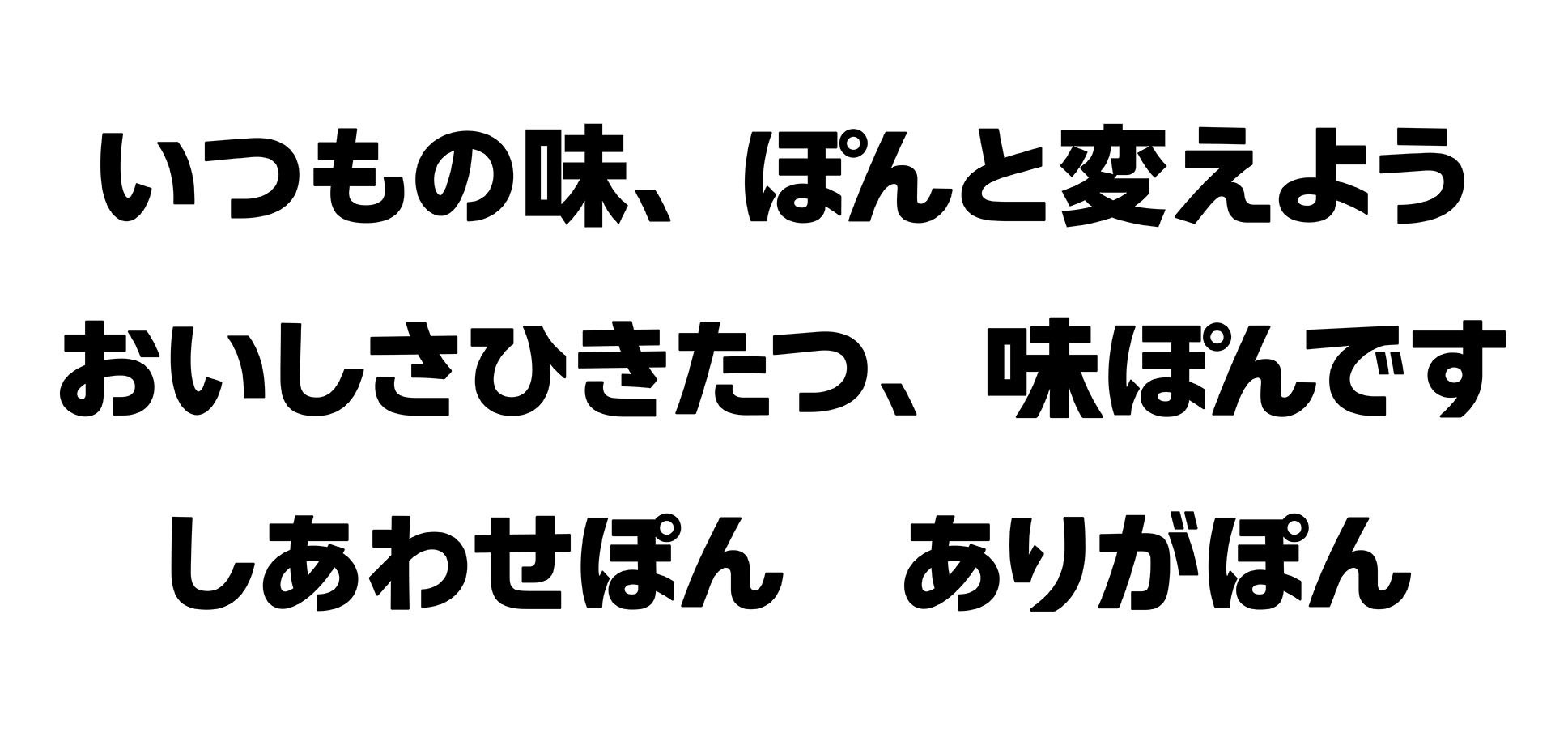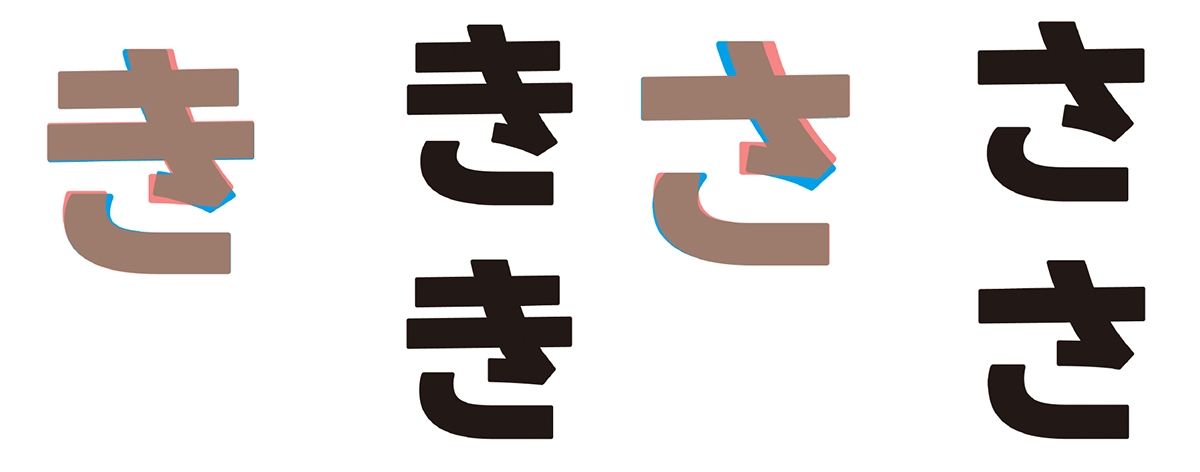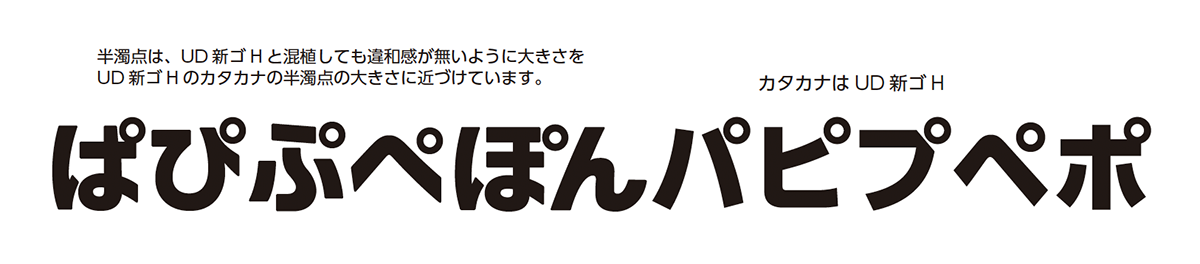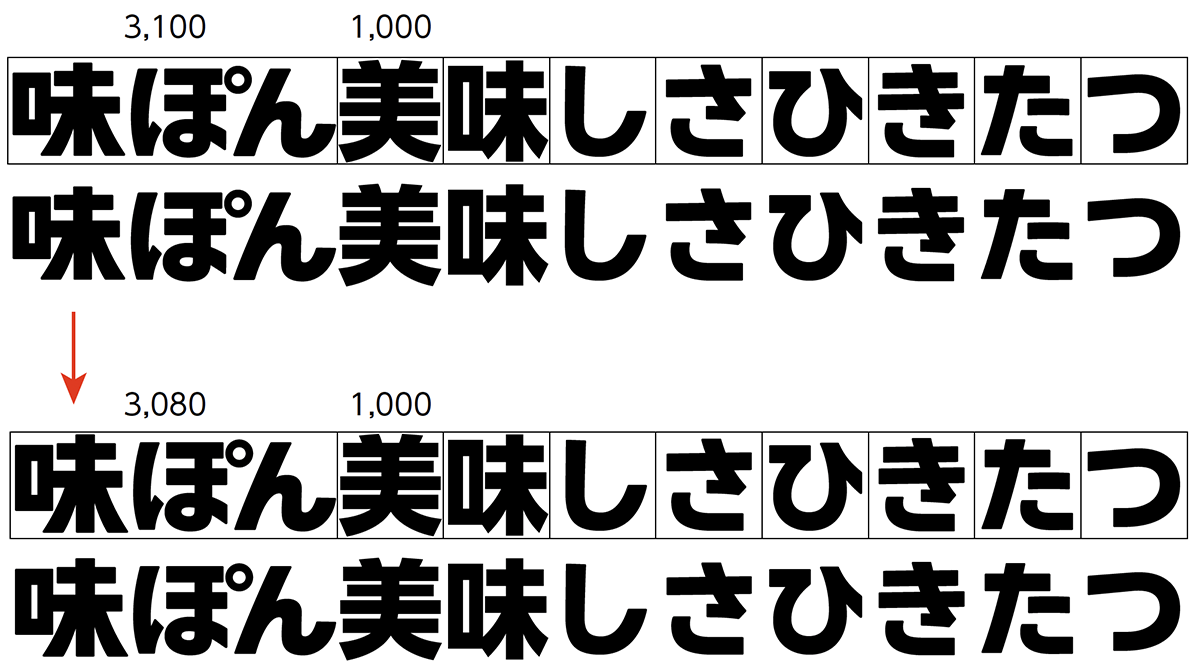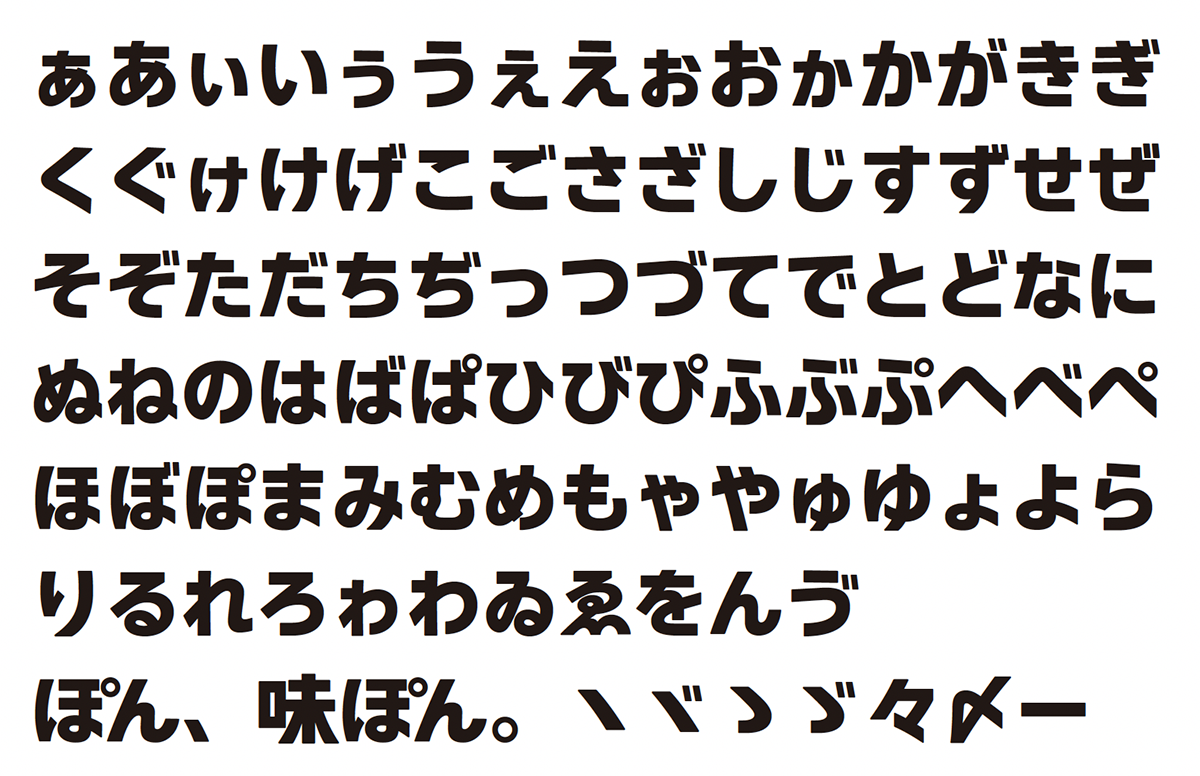
これからも愛される存在であり続けるため
「味ぽん」発売60周年の節目を彩る
オリジナルフォントを開発
長年にわたって日本の食卓を彩り、多くの人々に愛されてきた、株式会社Mizkan(以下ミツカン)の「味ぽん®」。そんな“国民的調味料”の発売開始60周年を記念し、2024年に商品ロゴをベースにしたオリジナルフォント「味ぽんフォント」をモリサワと企画・開発した。制作に至った経緯や、「味ぽん」ブランド強化に向けたフォントの活用法などについて、株式会社Mizkanマーケティング本部 マーケティング推進部 デザイン課の山田氏に話を聞いた。
「喜んでほしい」想いを原点にオリジナルフォント開発を決意
鍋専用調味料として1964年11月に誕生した「味ぽん」は、鍋以外の“かける”用途や調理の味付けなど活用の幅を広げ、ぽん酢市場シェアNo.1※1を占める、ミツカンの看板商品のひとつだ。かんきつ果汁と醸造酢、しょうゆが生み出す絶妙な味わいとともに、商品ラベルのロゴも消費者にとってなじみ深い存在となっている。
オリジナルフォントの開発は、発売60周年の節目に合わせて企画された。発案のきっかけは、「味ぽん」をテーマに夏休みの自由研究を完成させた男の子だったと、マーケティング本部 マーケティング推進部 デザイン課の山田氏は話す。「自由研究のお礼に、ラベルの『味』の部分に男の子の名前を入れた『オリジナル味ぽん』をプレゼントしたところ、とても喜んでくれて。この時は既存フォントを使用して作成したのですが、味ぽんらしいフォントで再現できれば、と考えたのが出発点になりました」。
それまでも企画などで「味ぽん」のロゴに寄せた名前入りラベルを制作したことはあったが、制作者が違うとどうしてもデザインにバラつきが生じてしまう。「味ぽん」ブランドの価値を守り、さらに高めていくためにも、一貫性のあるオリジナルフォントが必要ではないかという思いが芽生えたという。加えて、60周年のテーマ「お客様の声を形に」と通ずる部分があったことも、開発を決意する後押しとなった。
ただ「味ぽん」は一大ブランドであるだけに、この新しい試みには慎重な意見もあったという。「社内には、フォントを作ったところで本当に『味ぽん』らしさが出せるのか、という声もありましたが、モリサワさんにオリジナルフォントを制作する意義から活用の事例までさまざまな話をうかがい、それを元に説得を重ねました」。さらに、各部署にフォントの活用シーンをヒアリングして使い方のアイデアを提案に盛り込み、ゴーサインを引き出した。「モリサワさんには社内提案の段階でお声がけしたのですが、親身になって相談に乗っていただき、ぜひお願いしたいと思いました」と、山田氏は当時を振り返る。
「味ぽん」らしい“愛嬌”と混植時のバランスを追求
「味ぽん」のロゴは、線の起筆と終筆部分が水平、垂直で、かつ曲線の柔らかい丸みを持った、実直さと親しみやすさが同居したデザインとなっている。今回は、このロゴの文字をベースにした95文字のひらがなに加え、名前入りラベルなどへの展開を想定し、「ぽん」「味ぽん」のロゴをフォント(合字)として開発した。
実際の活用場面では漢字との混植も想定されるため、ロゴの形状と親和性が高いモリサワのUD新ゴと組み合わせる前提で制作をスタート。フォントデザインは、豊富な経験を持ち、UD新ゴ制作メンバーでもあったモリサワのタイプデザイナーが担当した。
ひらがなに関しては、柔らかく人懐っこい「味ぽん」の持つ“愛嬌”を表現するために、1字ずつ繊細なチューニングを施している。例えば「き」「さ」のようにはねがある文字はシャープな印象になりやすいため、最初のデザインから修正を重ね、はねの角度を緩やかにしている。同時に、UD新ゴと混植しても自然に見えるように文字のバランスを調整しており、例えば、半濁点の大きさは、UD新ゴのカタカナに近づけるなどしている。
また、元々扁平に作られている「味ぽん」ロゴは、そのままフォント化しようとすると横幅が規格のサイズに収まらず、混植時に違和感が生じてしまう。そこで、ロゴのイメージを保ちつつ横幅を縮め、「味」の天地を広げてUD新ゴのサイズ感に合わせた。
文字の細かい調整においては、「味ぽん」ロゴを制作したデザイナーがアドバイザーとして参画したことが大きかったと振り返る。「フォントデザインは独特で、何をどうすればより“らしさ”がでるのか、言語化して伝えるのが難しいところもありました。ロゴデザイナーの方に入ってもらったことで、テクニカルな部分や細かいニュアンスも、プロ同士のやり取りでスムーズに伝えられるようになりました」。
こうして「味ぽん」ロゴが持つ印象はそのままに、漢字やカタカナと混植してもバランスのよいオリジナルフォントが完成。山田氏は「何度も調整していただく中で、その都度味ぽんらしいデザインになっていく過程を感じることができました」と評価する。また、オリジナルフォントを制作したことで、フォントの理解をより深めたいと考えるようになったという。「モリサワさんにお願いして、デザインチームのメンバー全員が参加する勉強会を開いていただきました。フォントを作る過程や印刷に関するお話も伺うことができ、フォントの奥深さに触れることができました」。
ラベル印刷のプリンター導入も二人三脚で
完成した「味ぽんフォント」には、社内外から大きな反響があったという。「オリジナル名刺」を作成して取引先の方にお渡しすると興味を持ってもらえて、60周年の取り組みを説明するよいきっかけになりました。また、社内報に掲載した際には『名刺を作りたい』『グッズ展開してはどうか』と、普段「味ぽん」に直接関わっていない部署からも多くの反応やアイデアが寄せられ、改めて「味ぽん」は広く愛されている商品なんだな、と実感しました」
なかでもオリジナルフォント制作のきっかけでもあった、「名前入りの『オリジナル味ぽん』を作りたい」という声は多く、早速オリジナルラベルの制作に取り掛かることとなった。しかし、ここで大きな壁に直面する。「実際のラベルのオレンジ色は特色(色見本に合わせてインキを調合)なので、オンデマンドプリンターでは色が合わないんですね。かといってオフセット印刷にすると膨大なコストがかかってしまう。せっかくの計画が進まず、モリサワさんについ愚痴をこぼしたところ、お手伝いできますよ、と言っていただいて」。
印刷業界に根付いた営業活動で培った知見を生かし、モリサワの担当者が数社のプリンターを検証。山田氏と共にデモにも参加し、発色と合わせて操作の簡易さ、コストなどの要件を満たすエプソン社製のプリンターを導入した。
山田氏は「(モリサワは)フォント専門の会社だと思っていたので、守備範囲の広さに驚きました。導入したプリンターで印刷したラベルは実物と比べても見劣りしない出来で、本格的な活用はこれからですが、社内からは『家族に好評だった』『取引先に渡したい』といった声が届いています」と笑顔を見せる。「オリジナル味ぽん」や名刺のほか、愛知県半田市にあるMIM(ミツカンミュージアム)でのグッズ展開や、ECサイトでの名入れサービスなどさまざまなアイデアも浮かんでいるようで、「味ぽんフォント」の活用範囲はさらに広がりそうだ。
「『味ぽん』は長年大切にしてきたブランドです。変えてはいけないところは守りながらも、お客様に喜びや、ちょっとした驚きを届けるためには、同じところに留まっていてはいけないと考えています」。今後の「味ぽん」ブランドがどのような進化を遂げるか、注目していきたい。